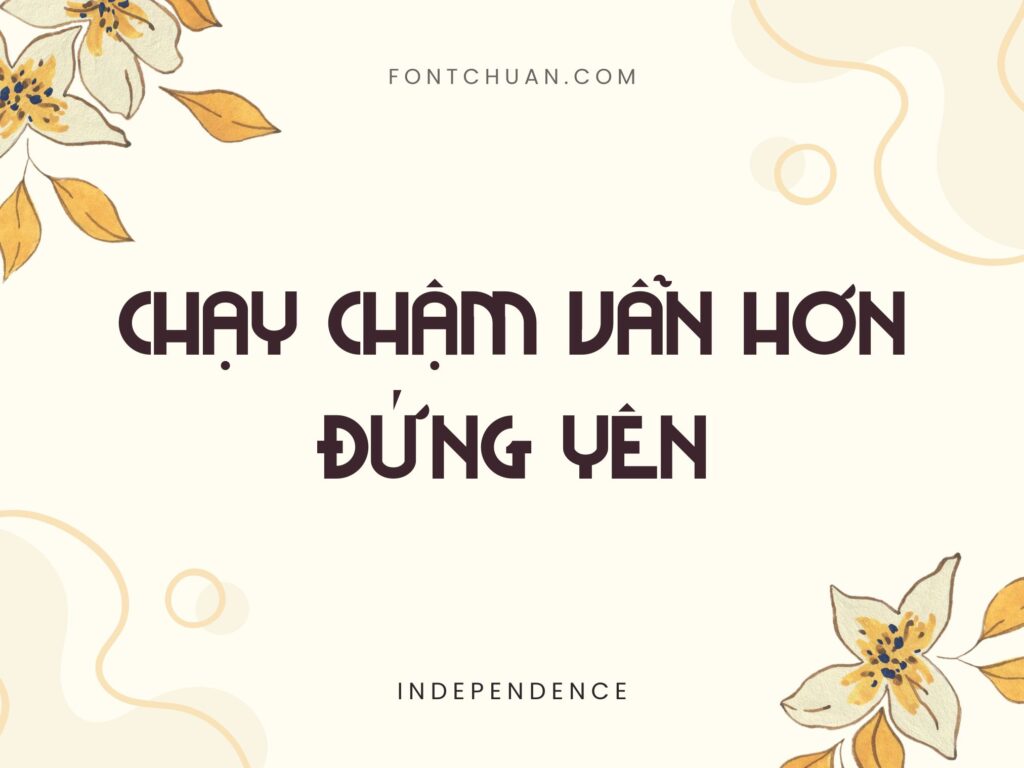
Doc Lap (Độc Lập) là một phông chữ dựa trên phong cách chữ đậm của các áp phích Việt Nam trong thời chiến, được thiết kế bởi Đặng Anh Khoa. Phông chữ này lấy cảm hứng từ Nghệ thuật Tuyên truyền, một công cụ hiệu quả trong kháng chiến chống đế quốc, nhằm khơi dậy lòng yêu nước và niềm vui thống nhất đất nước khi nhìn lại lịch sử dựng nước của Việt Nam. Với các đường nét mạnh mẽ, hình học và tự tin, Doc Lap phù hợp cho các thiết kế cần sự nổi bật và truyền tải thông điệp mạnh mẽ. Phông chữ này miễn phí cho cả sử dụng cá nhân và thương mại, giúp người dùng linh hoạt trong việc áp dụng vào các dự án khác nhau